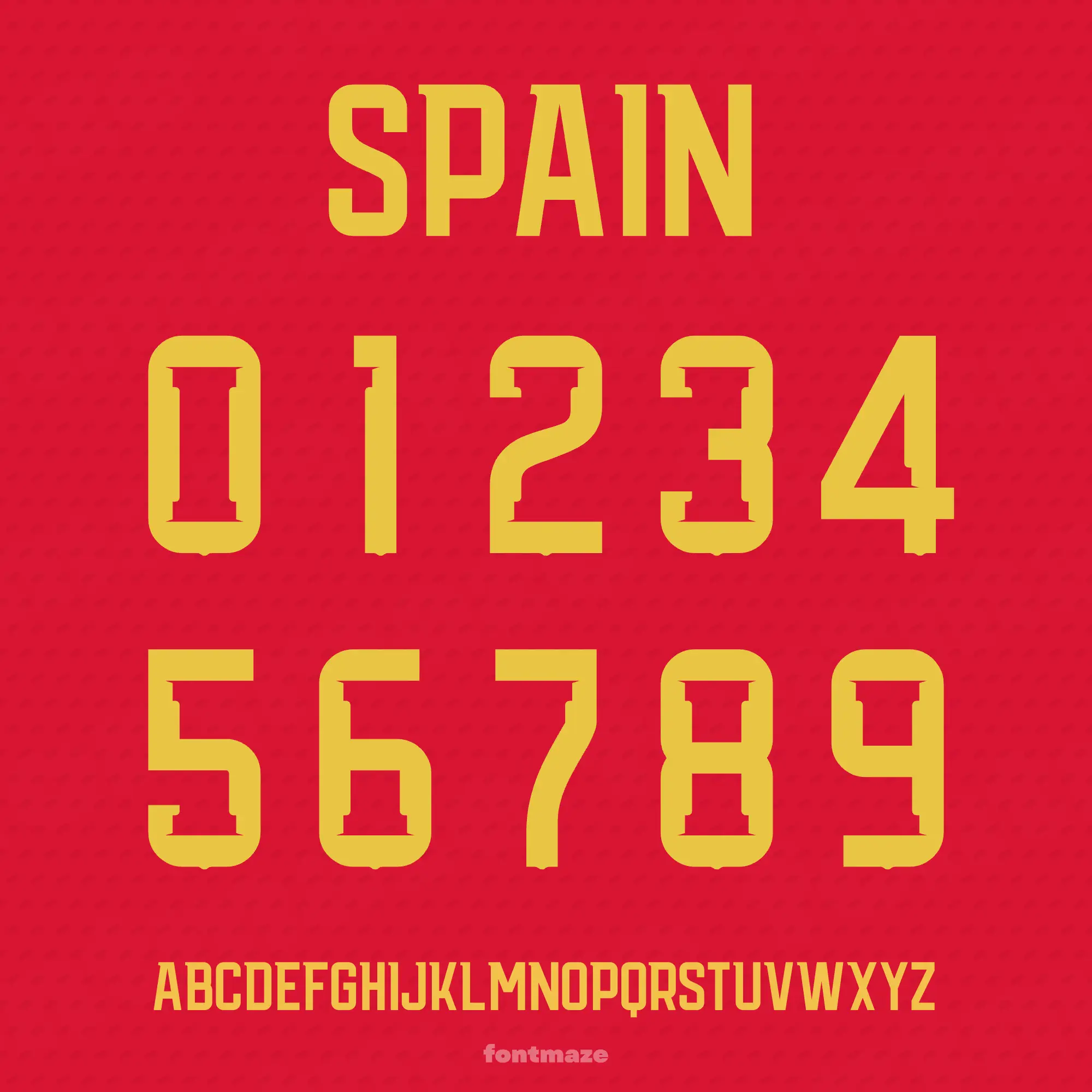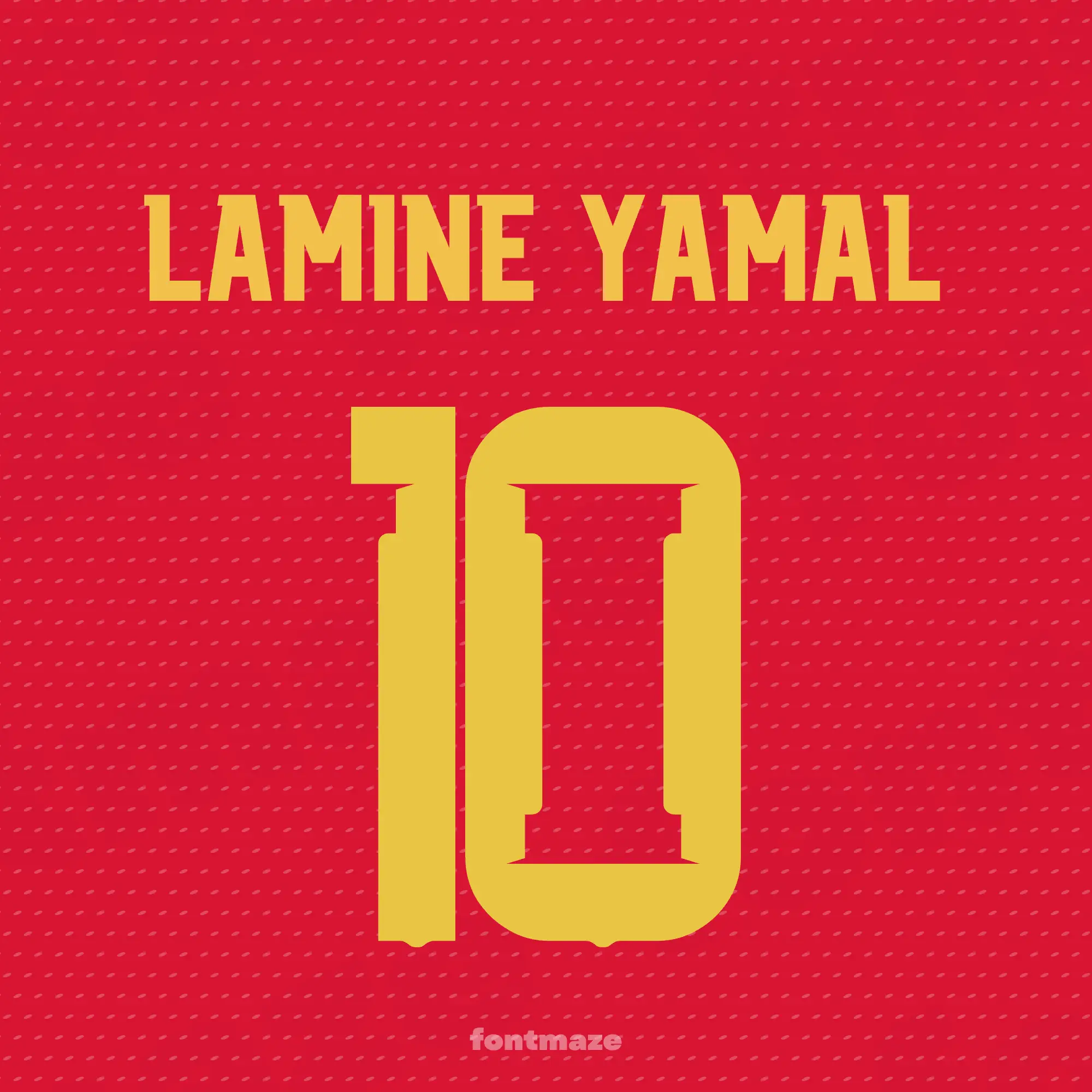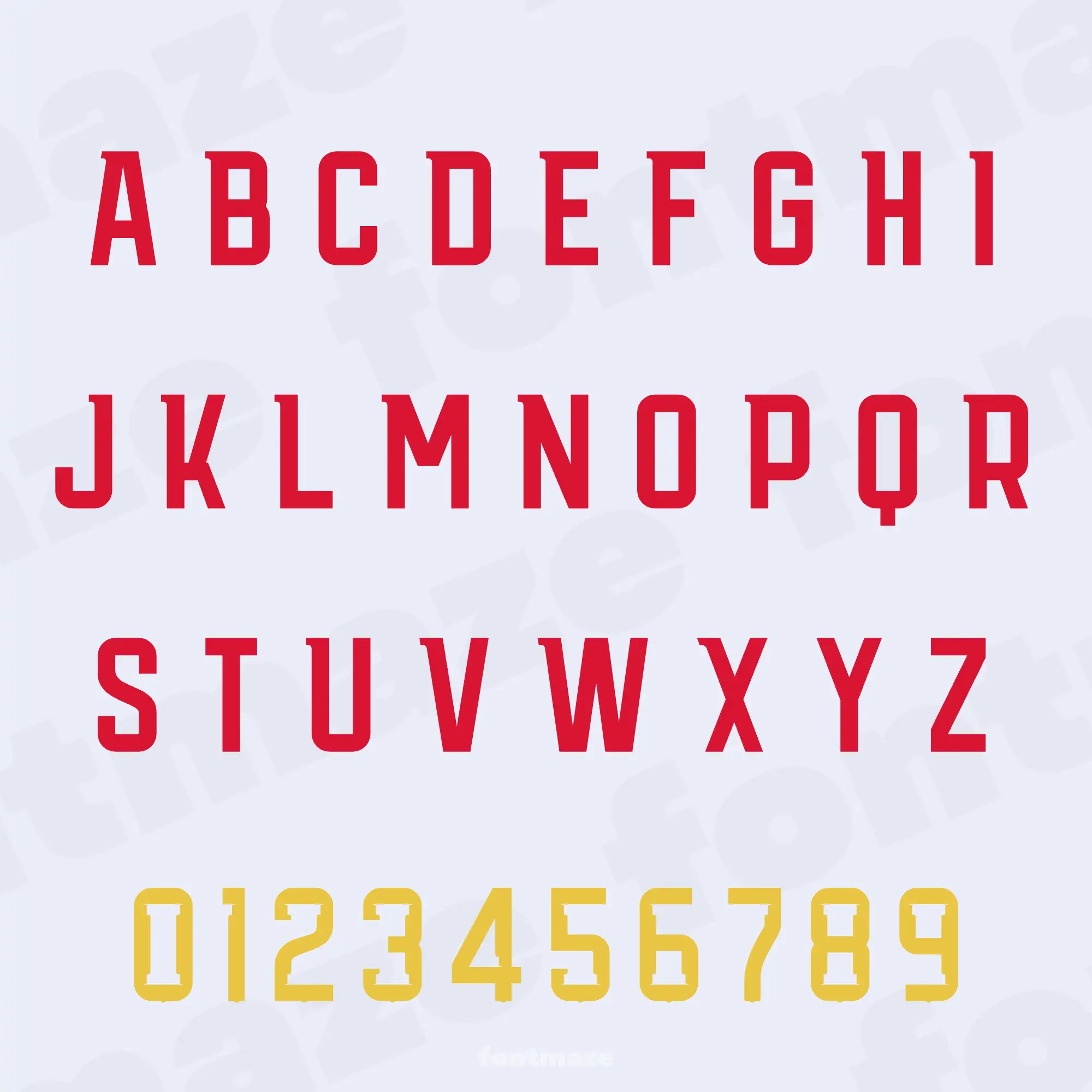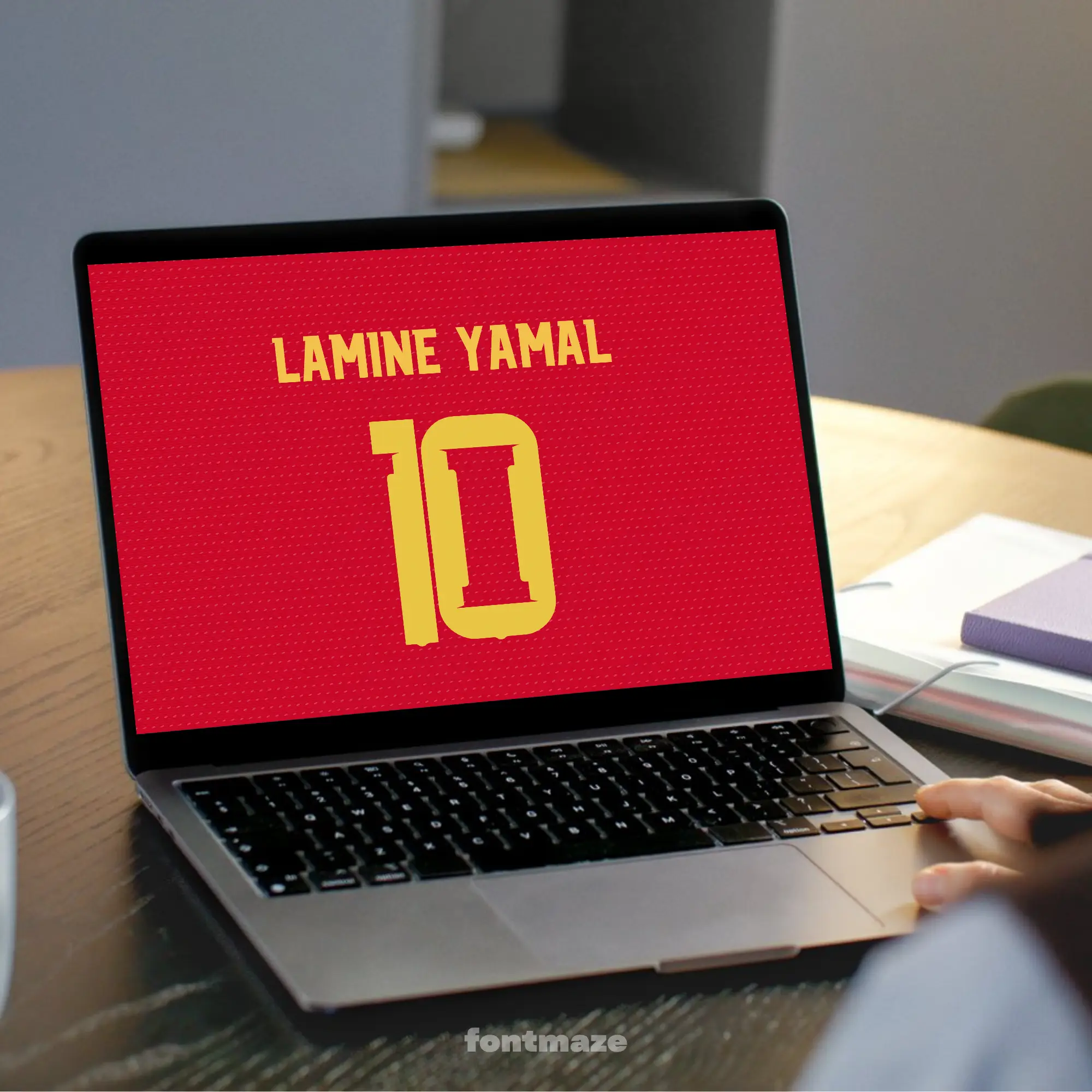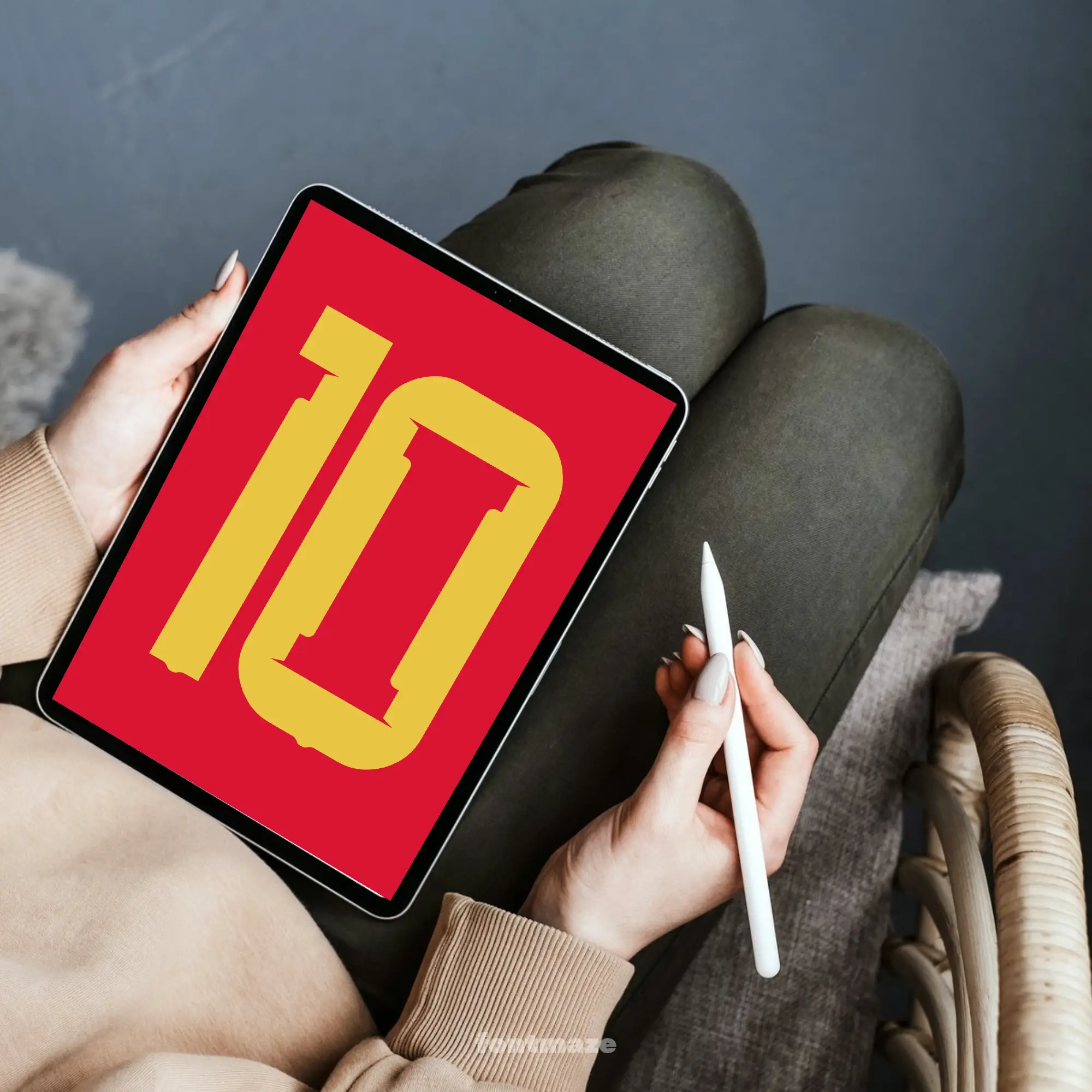
Fuente de fútbol de España, letras deportivas Mundial 2026
Haz que tu próximo proyecto destaque con Fuente de fútbol de España, una tipografía versátil y elegante creada para personas creativas.
Diseñada a mano en nuestro estudio con cuidado y atención al detalle, aporta un toque único y personal a tus creaciones.
Qué puedes crear con esta fuente
Usa Fuente de fútbol de España para gráficos de redes sociales, manualidades imprimibles, diseños de sublimación, pegatinas, logotipos, invitaciones, diseños deportivos, decoración de fiestas, proyectos escolares y descargas digitales.
La usé para una camiseta personalizada y los dorsales quedaron muy bien.
Muy práctica para poner nombres y números en equipaciones.